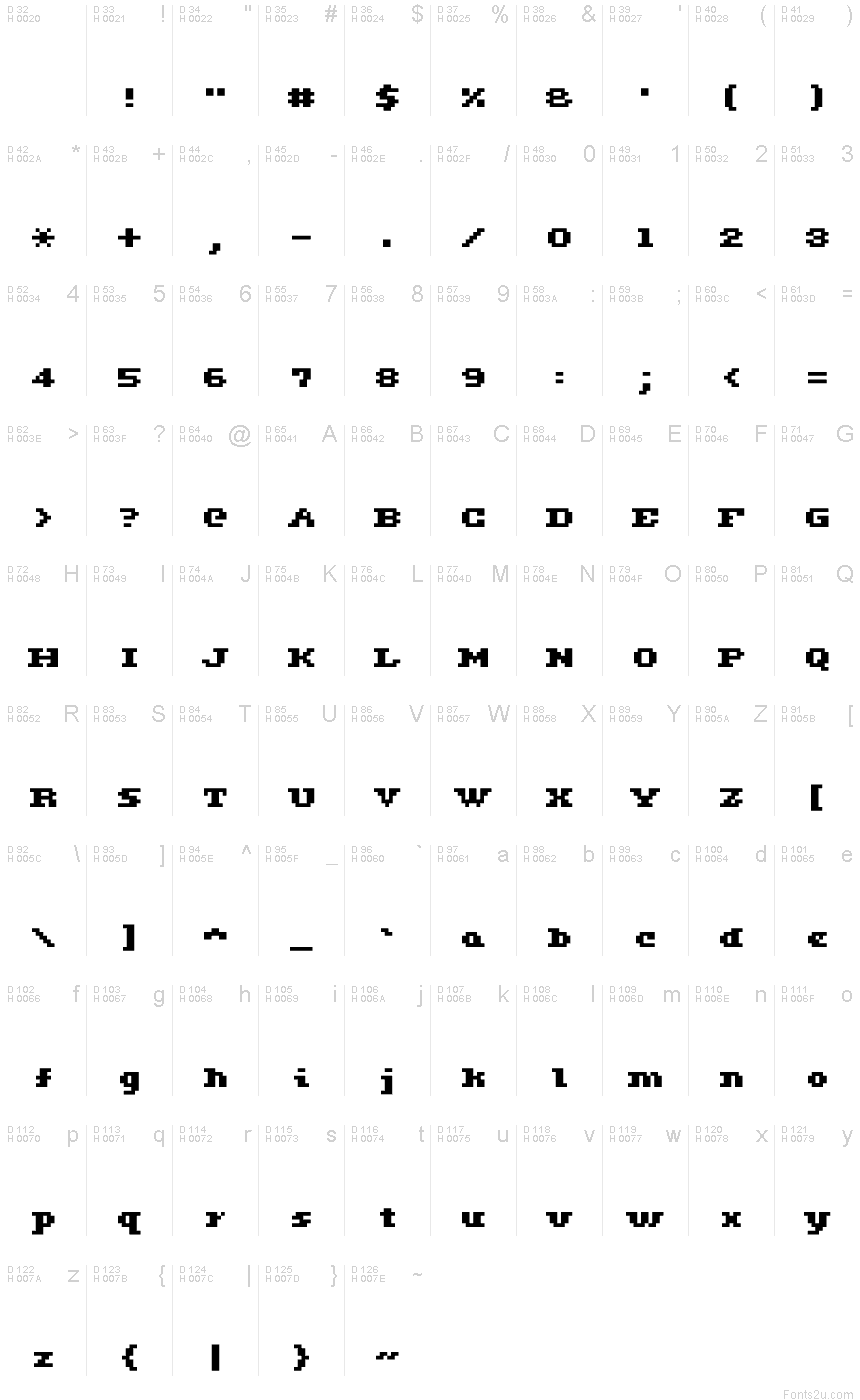
Podgląd czcionki ceriph 05_63
Ceriph 05_63 autorstwa Craiga Kroegera to darmowy bitmapowy krój szeryfowy z surowym klimatem wczesnych wyświetlaczy. Litery zbudowane są z wyrazistych kwadratowych pikseli, ale rytm nie jest czysto mechaniczny – przycięte rogi, małe płytkowe wypustki i stopniowane łączenia nadają mu zwięzły szeryfowy charakter, który wydaje się przemyślany, a nie surowy.
Naturalnie odnajduje się w interfejsach gier, nagłówkach zinów, na plakatach, banerach internetowych i ekranach tytułowych, gdzie darmowy font może wykorzystać ten kompaktowy klimat lo-fi. Użyj go do krótkich etykiet, ekranów ładowania, napisów na okładki lub małych logo, gdy szukasz pikselowego kroju, który ma w sobie nutę szeryfowej elegancji, a nie tylko zwykłą arcade'ową prostotę.